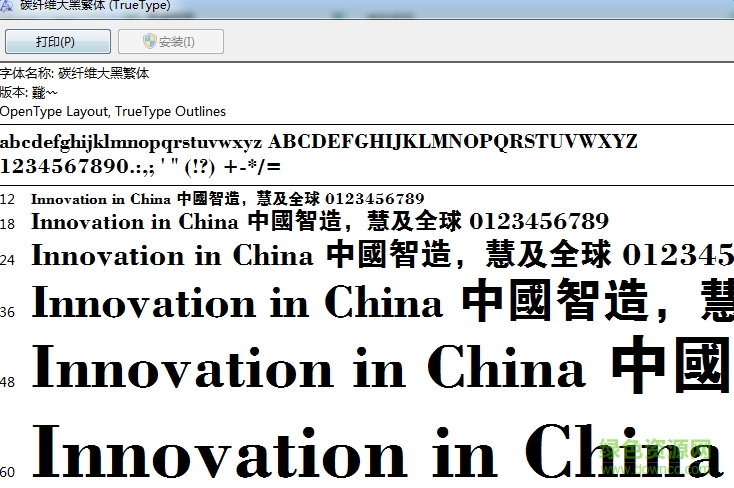
碳纖維大黑繁體
碳纖維大黑繁體是一款應(yīng)用于廣告設(shè)計(jì)方面的黑體字體,該字體線條非常的粗壯,字型極具個(gè)性,是一款不可多得的個(gè)性字體??蓮V泛應(yīng)用于平面設(shè)計(jì)、廣告設(shè)計(jì)、報(bào)紙雜志、正文標(biāo)題等領(lǐng)域,喜歡的網(wǎng)友可免費(fèi)進(jìn)行字體下載收藏。
碳纖維大黑繁體字體是一款超好用的個(gè)性字體,字體線條粗狂,給人一種大氣的感覺,有需要的用戶趕快來綠色資源網(wǎng)下載使用吧!